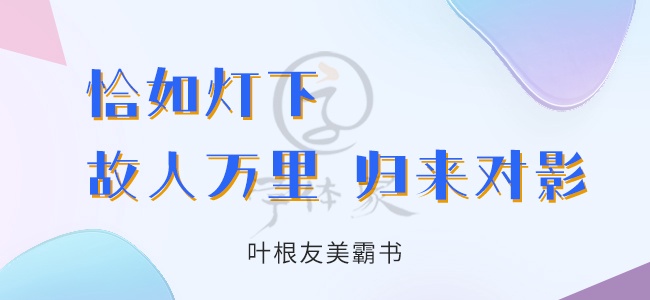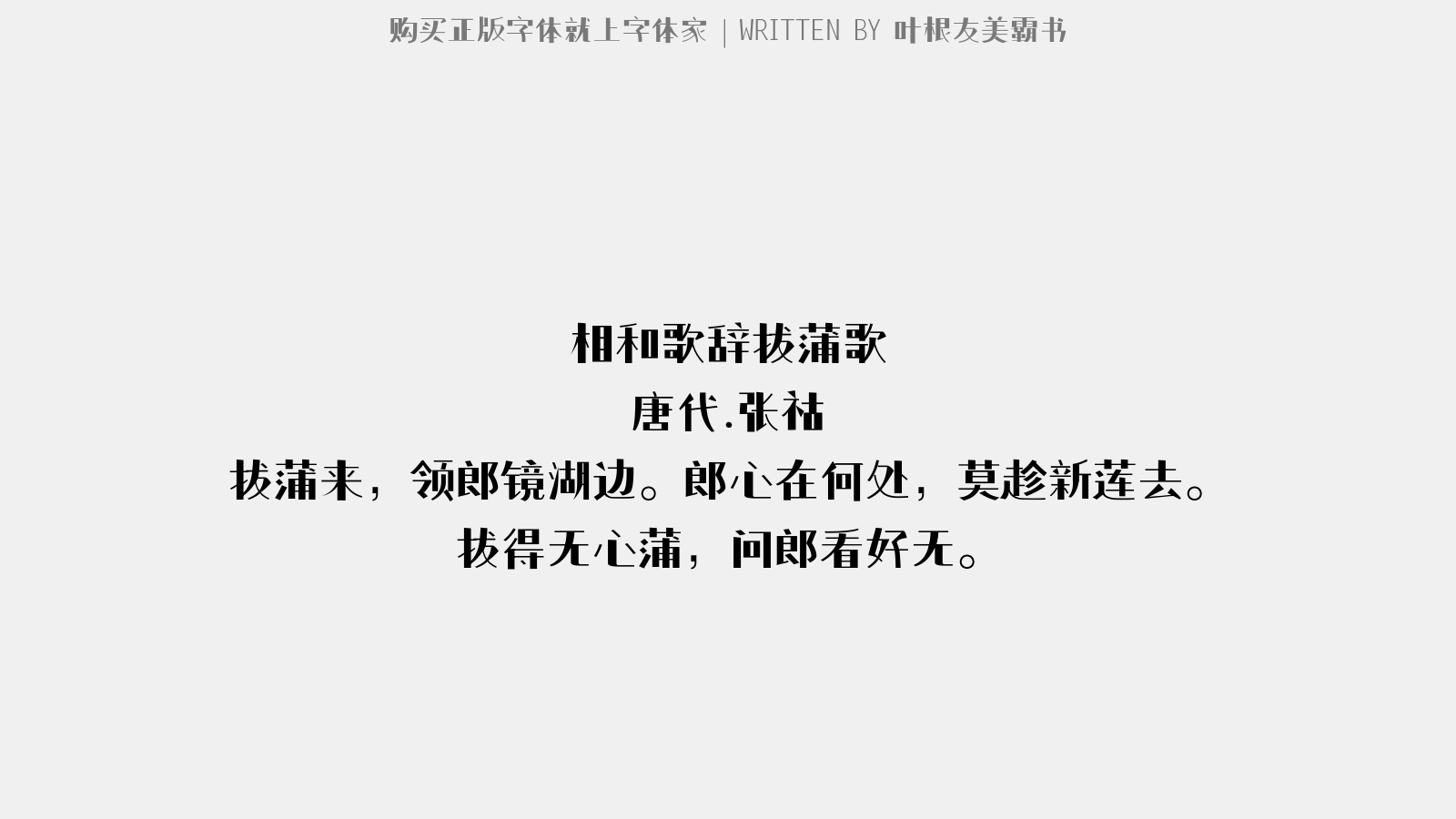
叶根友美霸书
字体作者:叶根友
字体名称:叶根友美霸书
字体字数:6763个汉字和26个英文大小写字母
字体家族:叶根友系列
书体类型:手写体、印刷体
字体公司:杭州贤书阁文化创意有限公司
字体就是要霸气点,这是一款2017年叶根友字体系列最新的字体,让这款字体霸占你的设计屏幕吧。
送皋法师
唐代.司空曙
江草知寒柳半衰,行吟怨别独迟迟。
何人讲席投如意,唯有东林远法师。
叶根友美霸书 - 送皋法师
相和歌辞。拔蒲歌
唐代.张祜
拔蒲来,领郎镜湖边。郎心在何处,莫趁新莲去。
拔得无心蒲,问郎看好无。
叶根友美霸书 - 相和歌辞。拔蒲歌
洞仙歌
宋代.卢祖皋
月痕霜晕,雪染冰裁翦。车马尘中甚曾见。自扬州吟罢,踏遍西湖,堪爱处,偏是情高韵远。
冷香惊梦破,姑射人归,图画空遗旧妆面。问何事东君,先与春心,还又是、容易飞花片片。对暮寒修竹哽无言,更画角层城,夜闻吹怨。
叶根友美霸书 - 洞仙歌
叶根友美霸书 - 大写字母/小写字母/数字